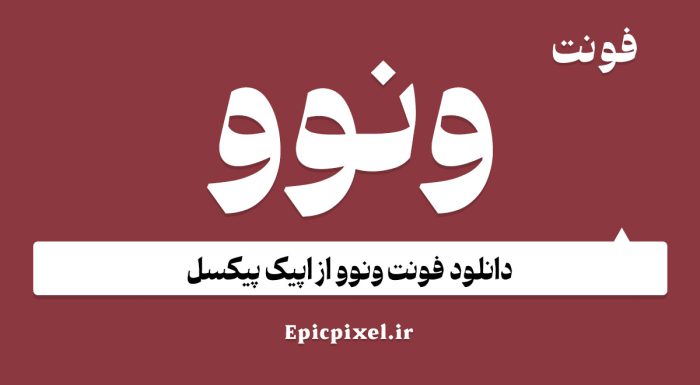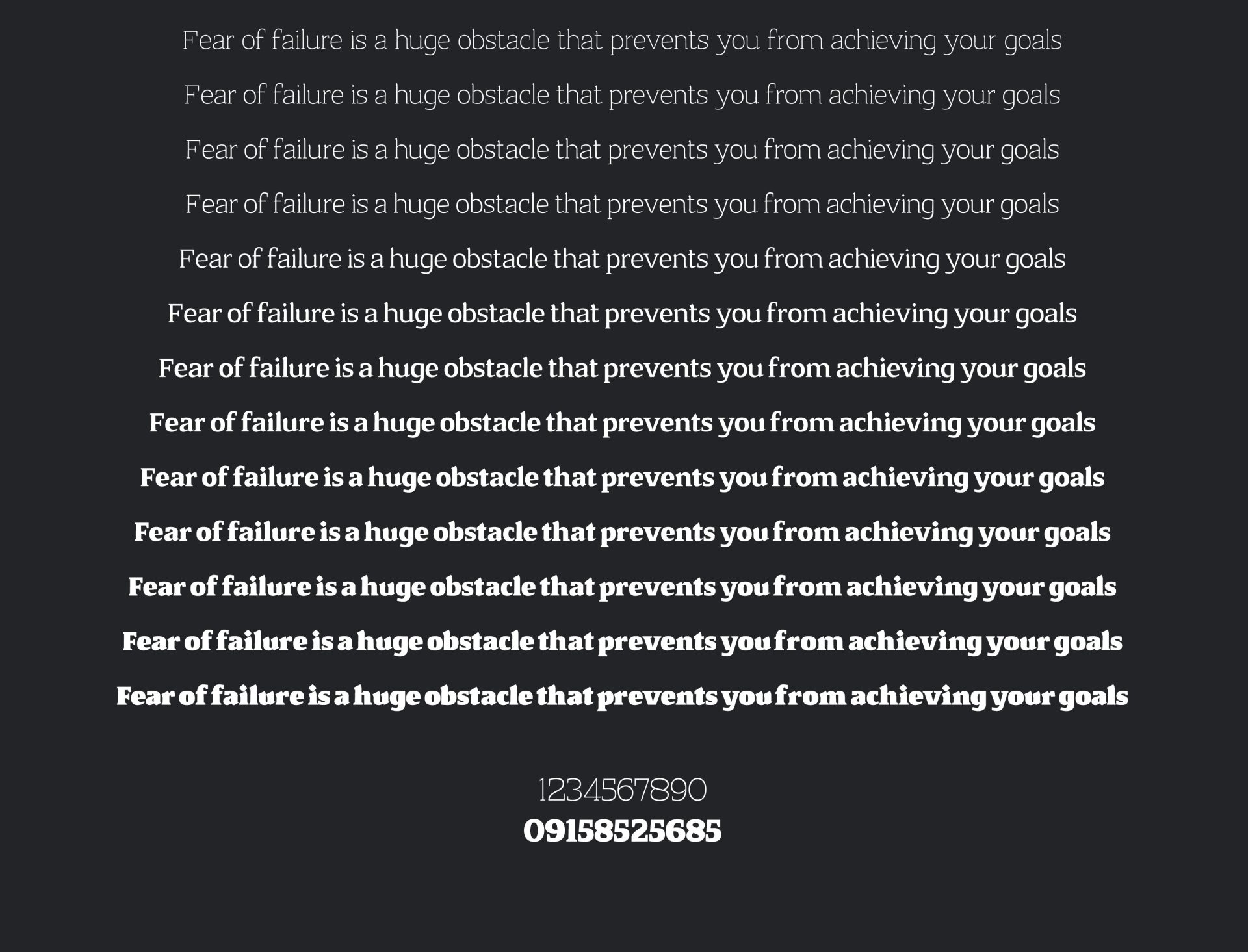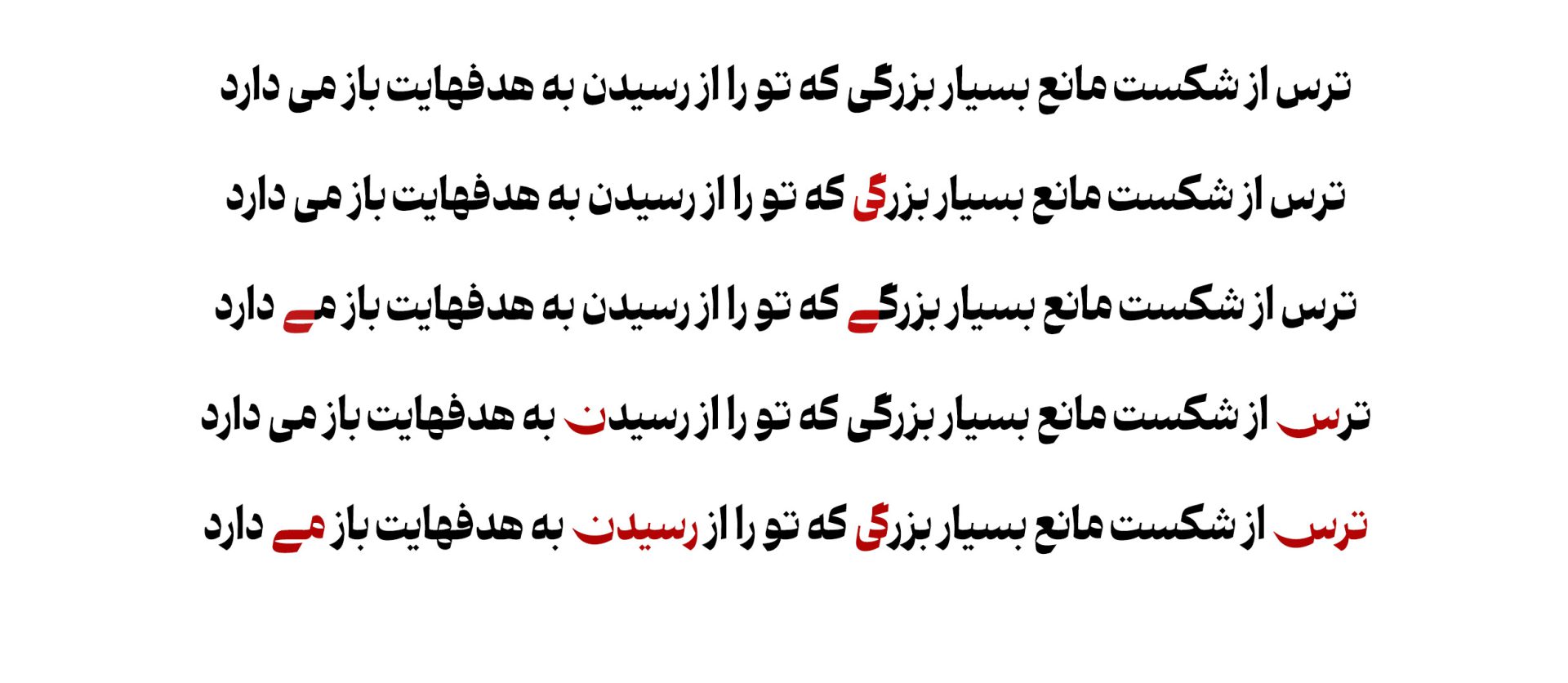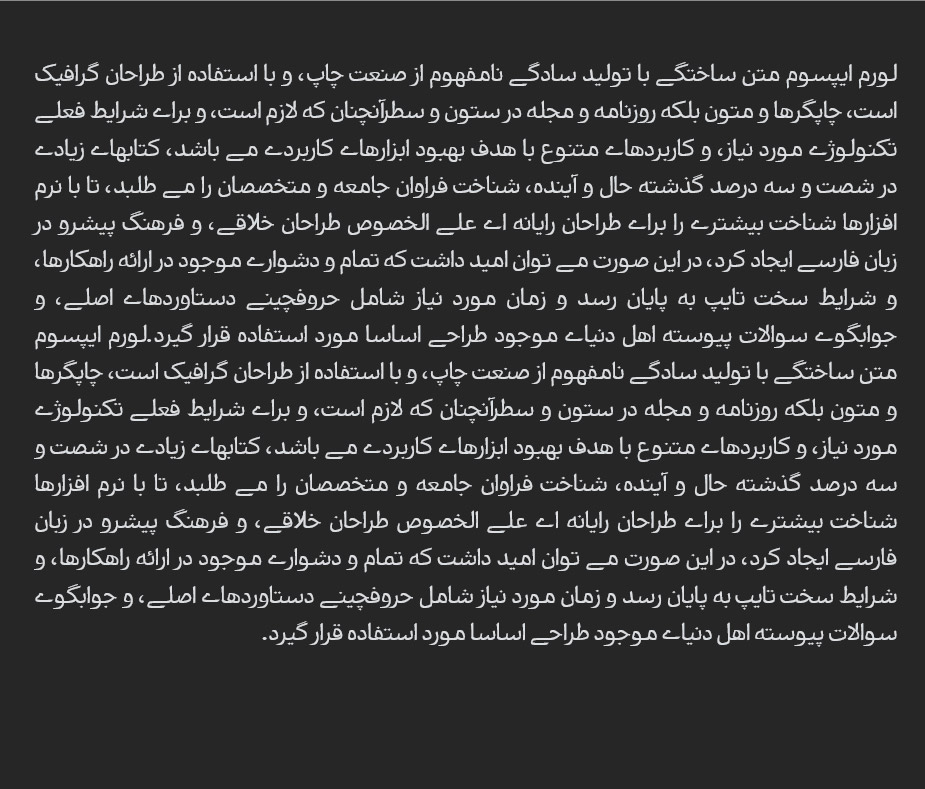
دنیای تایپ را با ونوو زیباتر کنید فونتی مدرن و جذاب برای هر سلیقه ای
فونت ها، جادوگران دنیای دیجیتال هستند. آنها میتوانند یک متن ساده را به یک اثر هنری چشمنواز تبدیل کنند و خواندن را به تجربهای لذتبخش بدل سازند. در میان انبوه فونتهای موجود، یکی از گزینههای درخشان که به تازگی توجه بسیاری را به خود جلب کرده است، فونت “ونوو” است.
ونوو مدرن، خوانا و دلنشین
ونوو، یک فونت بدون سرب با طراحی مدرن و مینیمالیستی است. حروف این فونت، ظریف و خوشتراشاند و خوانایی فوقالعادهای به متن شما میبخشند. علاوه بر خوانایی بالا، ونوو با داشتن وزنهای مختلف از جمله (Light, Regular, Bold) و ایتالیک، به شما امکان میدهد تا بر اساس سلیقه و نیاز خود، به تنوع و پویایی در طراحی خود دست پیدا کنید.
چرا از ونوو استفاده کنیم؟
دلایل متعددی برای انتخاب این فونت زیبا وجود دارد:
طراحی مدرن و مینیمالیستی: ونوو با ظاهر امروزی و ساده خود، به خوبی با ترندهای طراحی حال حاضر هماهنگ بوده و به کار شما ظاهری شیک و به روز میبخشد.
خوانایی فوقالعاده: حروف خوانای ونوو، تجربه خواندن لذتبخشی را برای مخاطب شما رقم میزند و به خصوص برای متون طولانی، گزینهای ایدهآل است.
تنوع و انعطافپذیری: وزنهای مختلف و ایتالیک ونوو، به شما اجازه میدهند تا از این فونت در بخشهای مختلف طراحی خود، از عناوین درشت تا متنهای ریز، استفاده کنید و به کار خود عمق و بعد ببخشید.
کاربردهای متنوع: ونوو برای طیف گستردهای از پروژههای طراحی مناسب است، از جمله وبسایتها، اپلیکیشنها، پوسترها، لوگوها، بروشورها و حتی طراحیهای چاپی.
کجا از ونوو استفاده کنیم؟
ونوو به دلیل ویژگیهای منحصر به فرد خود، در طیف وسیعی از پروژههای طراحی به کار میآید:
وبسایتها و اپلیکیشنها: طراحی رابط کاربری با ونوو، ظاهری مدرن و کاربرپسند به وبسایت یا اپلیکیشن شما میبخشد.
پوسترها و بنرها: ونوو با خوانایی بالا و ظاهر مینیمالیستی، برای جلب توجه مخاطب در پوسترها و بنرها گزینهای ایدهآل است.
لوگوها: خطوط صاف و خوانای ونوو، آن را برای طراحی لوگوهای مدرن و مینیمالیستی مناسب میکند.
بروشورها و کاتالوگها: ونوو، خواندن اطلاعات موجود در بروشورها و کاتالوگها را برای مخاطب تسهیل میکند.
طراحیهای چاپی: ونوو حتی برای طراحیهای چاپی مانند مجلات، کتابها و اسناد اداری نیز گزینهای مناسب است.
نکاتی برای استفاده از ونوو
برای استفاده بهینه از ونوو، به این نکات توجه داشته باشید:
از وزنهای مختلف برای ایجاد سلسله مراتب بصری استفاده کنید.
برای تاکید بر کلمات و عبارات کلیدی، از ایتالیک استفاده کنید.
فضای کافی بین حروف و خطوط در نظر بگیرید تا خوانایی حفظ شود.
ونوو را با رنگهای مناسب ترکیب کنید تا تاثیرگذاری آن را افزایش دهید.
ونوو را در کنار فونتهای دیگر به کار ببرید، اما در استفاده از فونتهای متعدد زیادهروی نکنید.
ونوو، با طراحی مدرن، خوانایی فوقالعاده و تنوع و انعطافپذیری خود، به سرعت به یکی از محبوبترین فونتهای طراحان تبدیل شده است. اگر به دنبال فونتی هستید که به کار شما ظاهری امروزی، زیبا و خوانا بدهد، ونوو انتخابی عالی است.